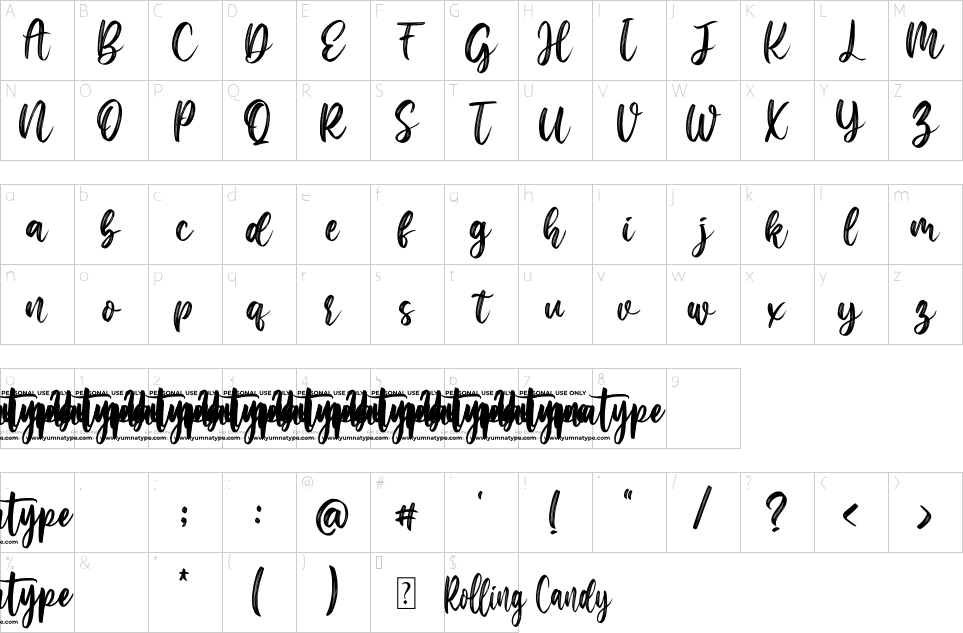
A Rolling Candy Font é uma escolha perfeita para designers que buscam uma tipografia fresca e alegre para seus projetos digitais. Com suas formas delicadas e cores suaves, essa fonte traz um toque de leveza à sua página ou design. Criada pela Yumna Type, esta elegante fonte pode ser usada tanto no Windows quanto no Mac. Com uma facilidade única em se adaptar a diferentes estilos, Rolling Candy é adequada para criar textos coloridos e criativos. Foram mais de 19 mil downloads dessa fonte, o que mostra sua popularidade entre designers. Se você está procurando por um estilo descontraído e sofisticado, a Rolling Candy Font pode ser a escolha perfeita para tornar seu projeto único.